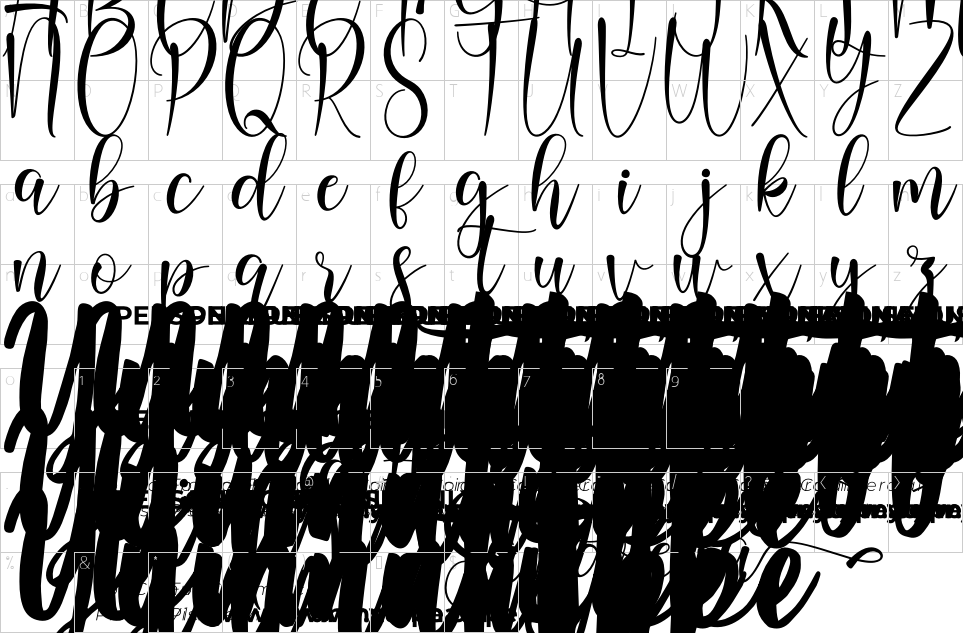
A Sandreya é uma fonte disponível de graça, projetada pelo designer Yumna Type. Suavemente elegante e com um toque moderno, essa fonte é uma ótima escolha para qualquer projeto de design gráfico. Com seus 1,655 downloads, é evidente que muitos designers têm encontrado valor em seu estilo versátil. Seja para o texto de seu site ou o design de sua capa de livro, Sandreya traz uma beleza minimalista e uma dinâmica atraente. Ideal tanto para designers gráficos quanto para web designers, essa fonte garante uma experiência de leitura agradável em ambientes Windows e Mac. Download Sandreya e adicione um toque único e moderno ao seu próximo projeto.